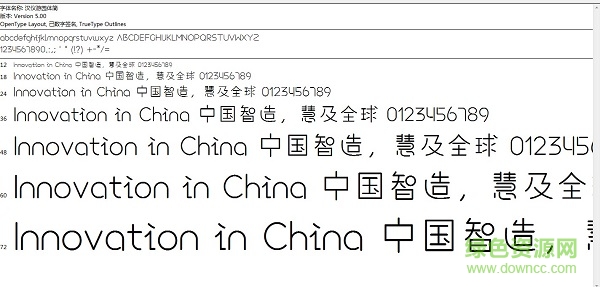
漢儀游園體字體包含了漢儀游園體簡(jiǎn)和漢儀游園體w兩款,該字體線條圓潤(rùn),字形別致,既具有藝術(shù)氣息又帶有童趣,可用于影視海報(bào)或兒童主題的廣告設(shè)計(jì)方面,本站已經(jīng)為大家打包好了,下載解壓即可使用!
為了能夠突顯園林的美學(xué)特征,在字體筆畫的設(shè)計(jì)上,以園林中各元素的造型為借鑒,意象性的在字體中表現(xiàn)園林的形態(tài)。適合產(chǎn)品畫冊(cè)、產(chǎn)品包裝設(shè)計(jì)、海報(bào)設(shè)計(jì)、網(wǎng)頁(yè)標(biāo)題設(shè)計(jì)等領(lǐng)域!